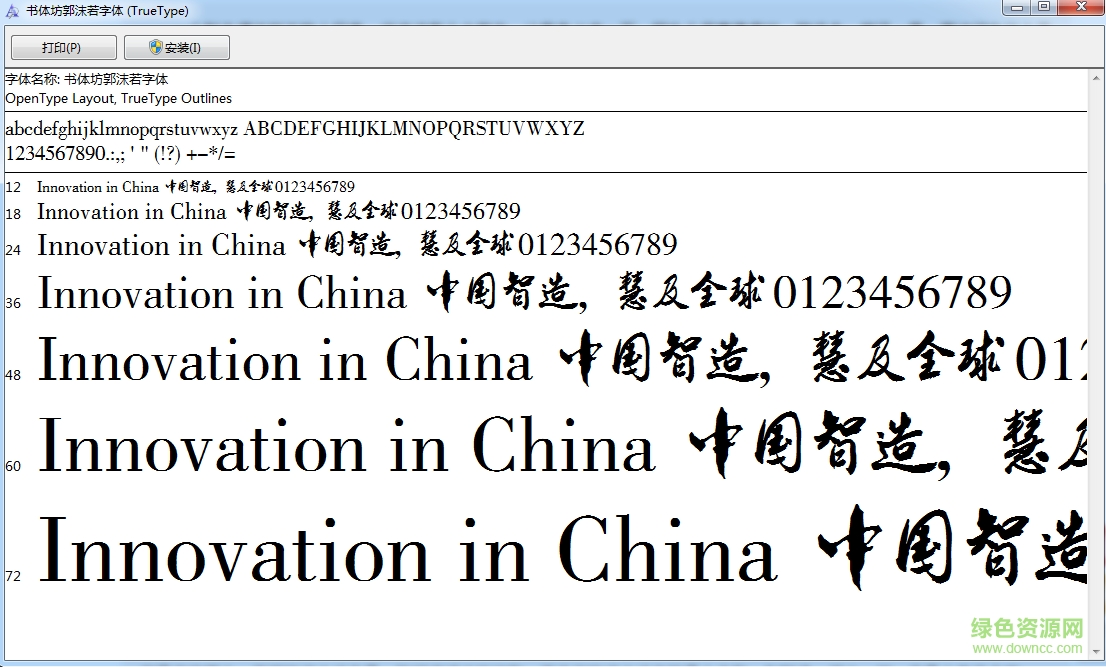
書體坊郭沫若字體是一款很有名人風(fēng)范的書體坊字體,飄逸的毛筆書法字體、黑體深沉的設(shè)計(jì),讓你的排版設(shè)計(jì)、創(chuàng)意便捷更顯優(yōu)雅之風(fēng)、文化內(nèi)涵,綠色資源網(wǎng)歡迎大家免費(fèi)下載!
在書法藝術(shù)方面,郭沫若同樣成就不凡,在現(xiàn)代書法史上占有重要地位。郭沫若以“回鋒轉(zhuǎn)向,逆入平出”為學(xué)書執(zhí)筆8字要訣。其書體既重師承,又多創(chuàng)新,展現(xiàn)了大膽的創(chuàng)造精神和鮮活的時(shí)代特色,被世人譽(yù)為“郭體”。郭沫若以行草見長,筆力爽勁灑脫,運(yùn)轉(zhuǎn)變通,韻味無窮;其楷書作品雖然留存不多,卻尤見功力,氣貫筆端,形神兼?zhèn)?。郭沫若在書法藝術(shù)上的探索與實(shí)踐歷時(shí)70余年。青年郭沫若的書法得到社會(huì)承認(rèn),始于辛亥年間。
新中國成立以后,郭沫若在繁重的國事之余從事更為豐富的書法創(chuàng)作。他慷慨為人,博識(shí)廣聞,為全國各地名勝古跡、工礦學(xué)校、以及社會(huì)各界、海內(nèi)外友人留下難計(jì)其數(shù)的辭章墨寶。其書法作品數(shù)量之多,影響之廣,少有出其右者。為紀(jì)念建國15周年而創(chuàng)作的巨幅書法作品是郭沫若書法作品的代表作之一。
在他的書法作品中,處處透射出一種“文”的氣息,寵萬端于胸中,幻化出千種思緒,從筆端涓涓流出,生成與他詩、文、史種種學(xué)問修養(yǎng)相融合的化境,以書法的外化形式展現(xiàn)給讀者。